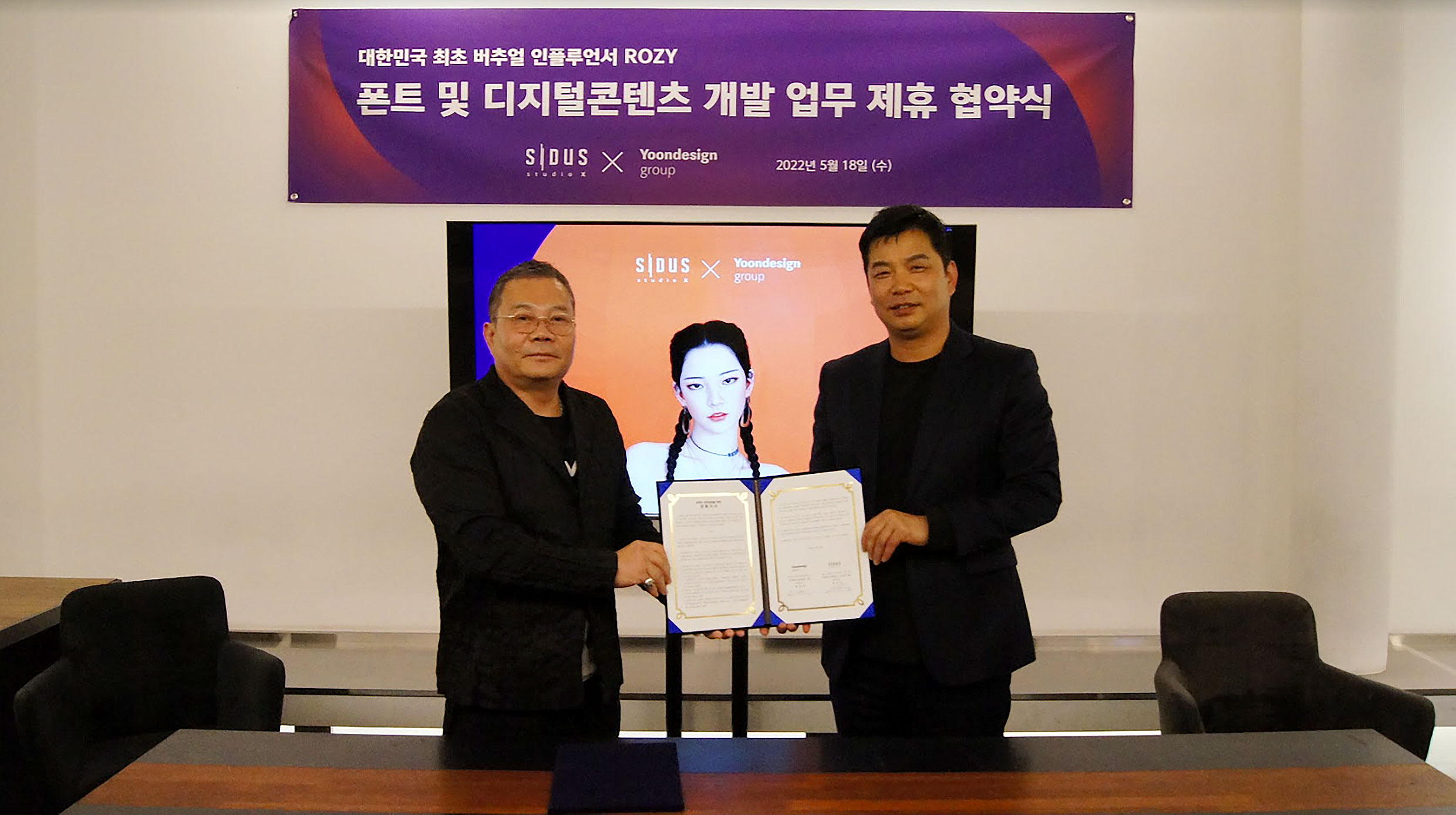
MZ세대가 사랑하는 버추얼 인플루언서 ROZY 브랜드 폰트, ㈜윤디자인그룹이 만듭니다
버추얼 인플루언서 ROZY 브랜드 폰트 및 디지털콘텐츠 개발 업무 제휴 협약식
㈜윤디자인그룹이 싸이더스 스튜디오 엑스와 함께 로지 브랜드 폰트 및 디지털 콘텐츠 개발에 나섰습니다. 이에 지난 5월 18일 업무 협약을 체결했죠.
로지(ROZY)는 2020년에 첫선을 보인 우리나라 최초의 버추얼 휴먼이자 버추얼 인플루언서입니다. 싸이더스 스튜디오 엑스가 MZ세대가 좋아하는 셀레브리티를 분석해 3D 기술로 로지를 탄생시켰어요. 그래서일까요? 현재 약 13만 명의 팔로워를 보유한 로지는 특히 MZ세대에게 사랑받으며 광고계에서도 큰 인기를 얻고 있죠.
그런 로지만의 시크하고 독특한 매력이 묻어나오는 브랜드 폰트를 윤디자인그룹이 개발할 예정입니다. 폰트 속에 숨어있는 로지와 관련된 딩벳이나 특수기호와 같은 요소들을 찾아내는 재미도 있을 거예요. 로지 브랜드 폰트는 디지털과 아날로그를 동시에 즐기는 MZ세대의 공감을 불러일으키고, 브랜드 폰트라는 소통의 도구가 되어 로지를 더 친근하게 느낄 수 있는 계기가 될 겁니다.
로지를 더 로지답게 만드는 브랜드 폰트, 어떤 모습으로 완성될지 기대되지 않으신가요?
로지 브랜드 폰트는 10월 출시 예정이며, 로지가 직접 쓴 듯한 ‘로지 손글씨 폰트’도 개발할 목표를 가지고 있습니다. 또한, 향후 다양한 굵기의 폰트 패밀리로의 확장도 고려 중이니, 많은 기대 부탁 드려요!